输入名字,挑一个颜色,下载 PNG。就这么简单,大约十秒钟。
这些全部出自同一个宝可梦字体生成器,只是从列表里换了不同的风格。什么都不用装,也不用注册。
怎样做出宝可梦文字
第 1 步:输入名字
打开生成器,把示例文字换成你要的内容:名字、队名、频道名、标题。你一边输入,字母就一边重绘。
第 2 步:挑选配色
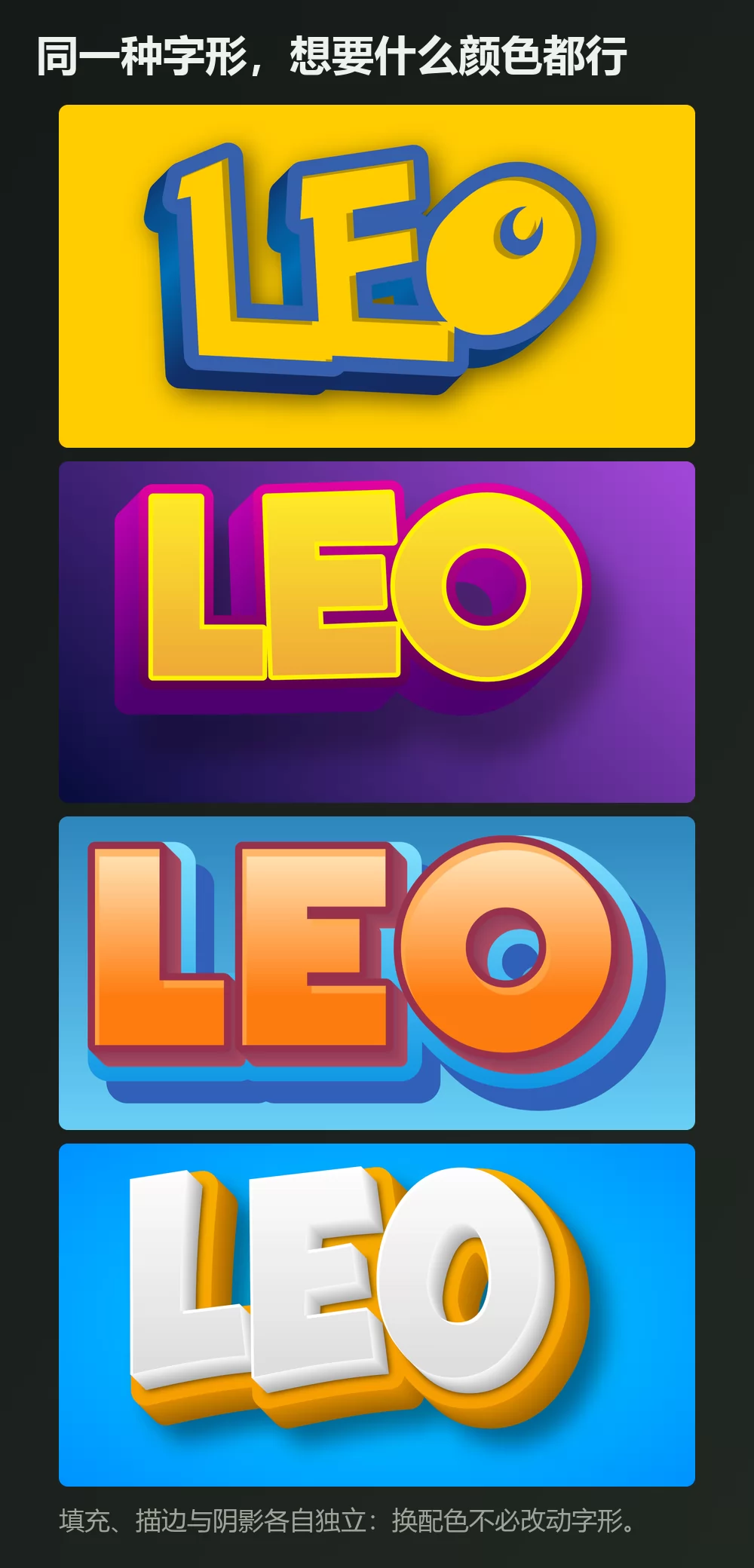
「样式」标签下有三个面板,各司其职:
- 3D 与填充负责字母本身的颜色:纯色、渐变或图案。
- 描边负责边框,包含两种立体描边。正是那圈深蓝色的边,让黄色字母读起来像宝可梦,而不是一个普通的黄色单词。
- 阴影涵盖投影、外阴影和内阴影,可调模糊与不透明度。
黄字配蓝边是这部作品的配色,但这个字形换成任何配色都成立。
第 3 步:选择尺寸
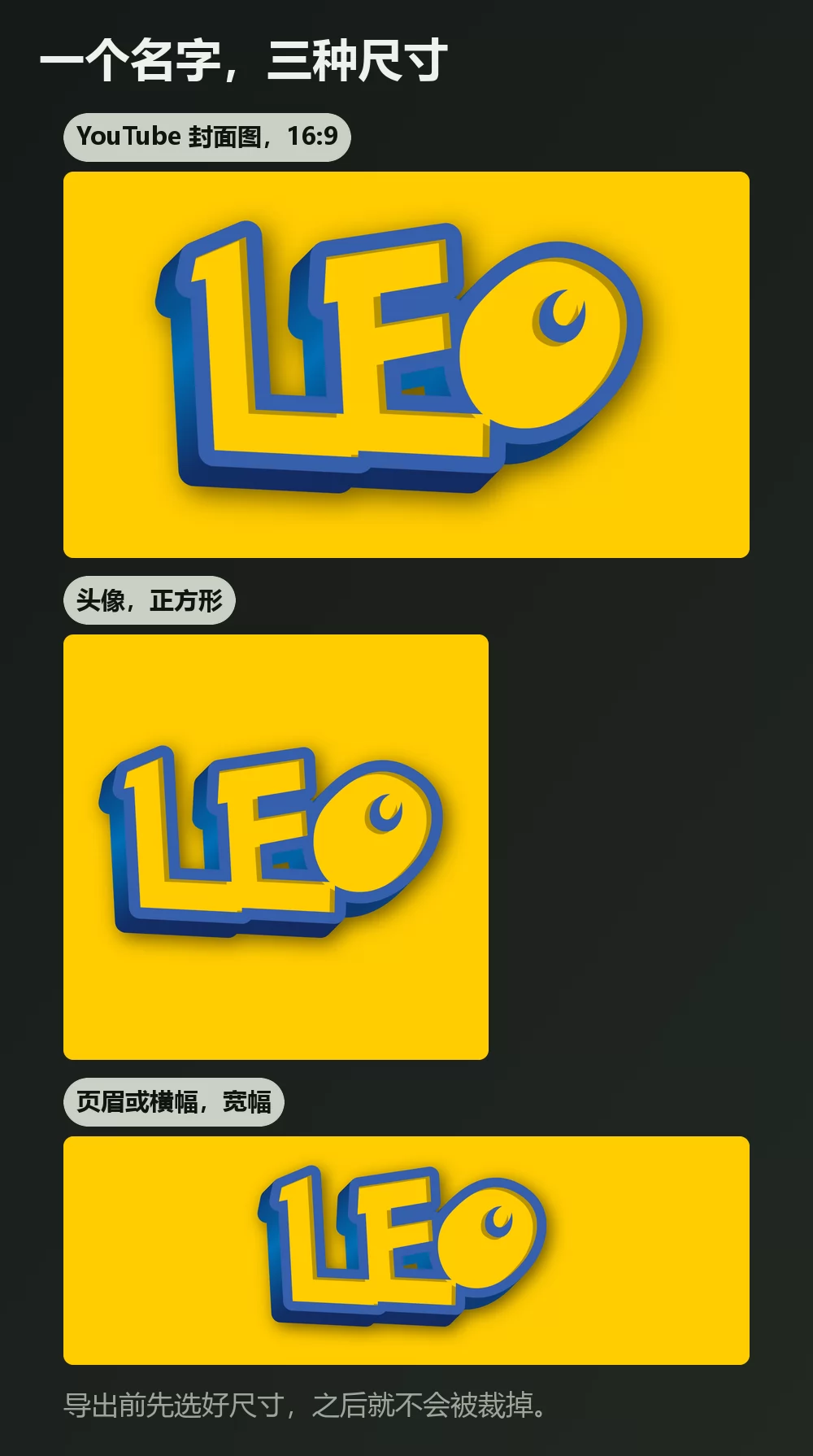
导出前先定好尺寸,之后就不会被裁掉。视频封面用 16:9,头像用正方形,页眉用宽条。
第 4 步:下载
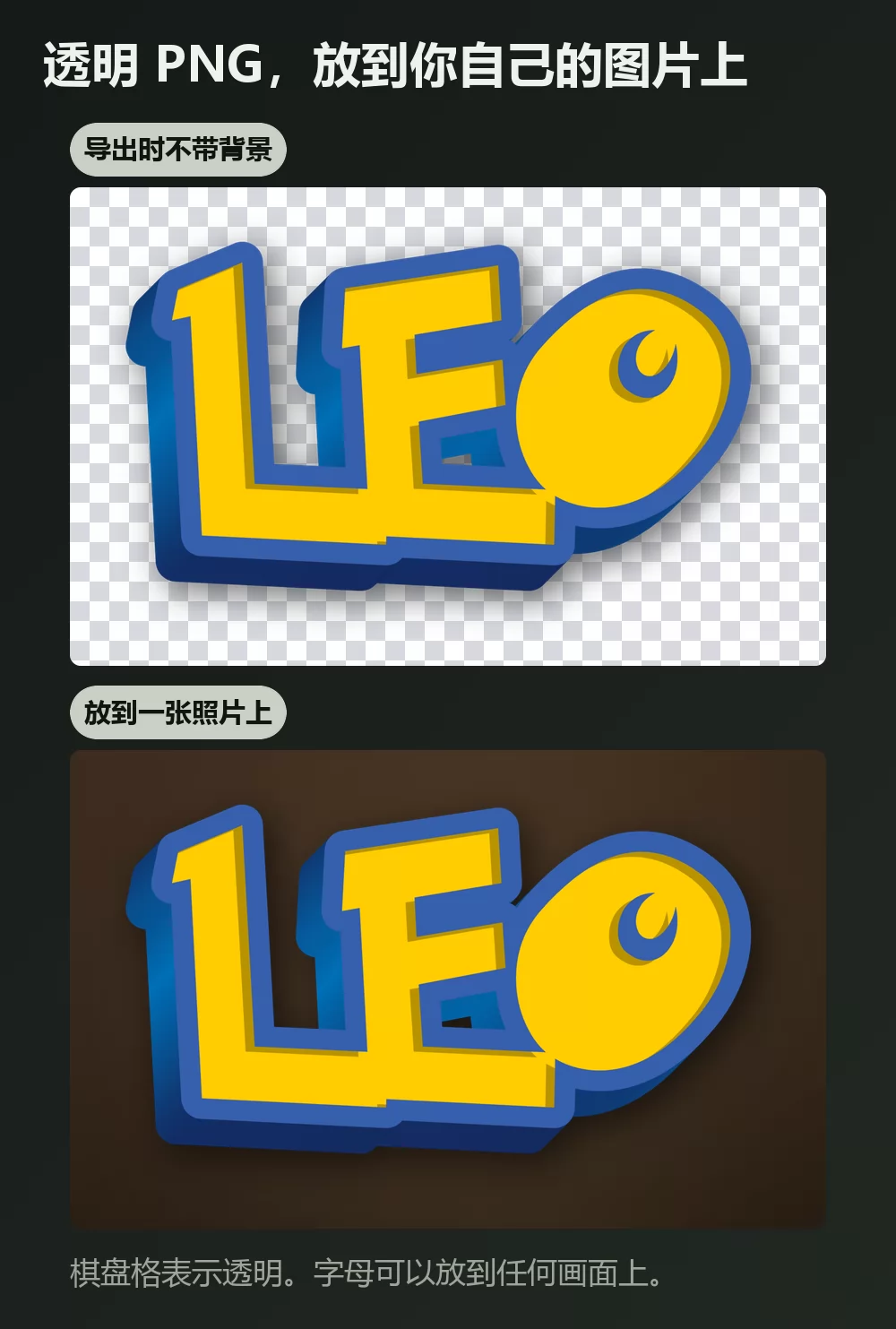
在「下载」标签里选透明 PNG,如果你打算把字母放到自己的截图、照片或封面上。这是大多数人漏掉的选项,也正是它让成品看起来是做出来的,而不是贴上去的。
名字一长,很快就占满宽度
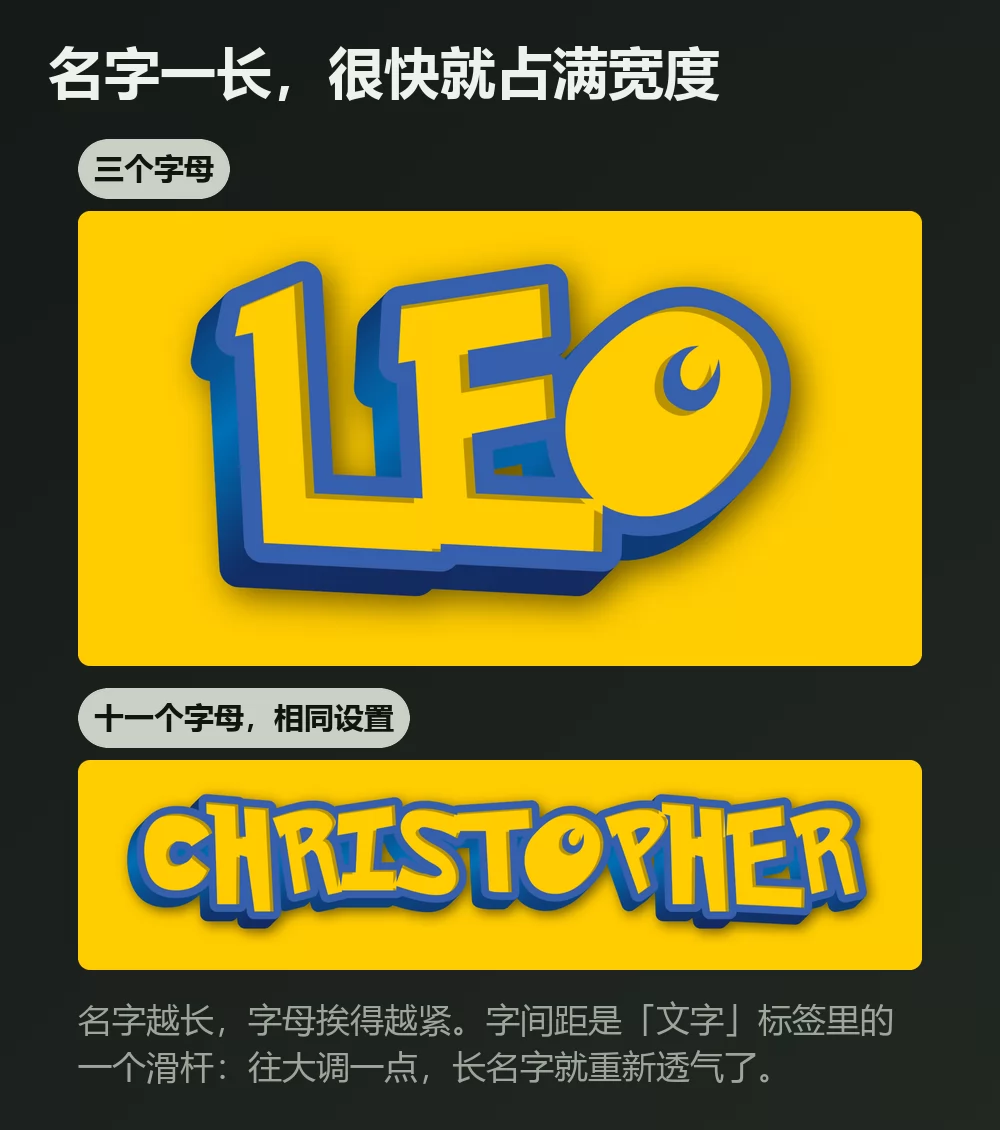
字母越多,挨得越紧。字间距是「文字」标签里的一个滑杆:往大调一点,长名字就不再显得局促。同一个标签里还有缩放、行高、弯曲和旋转。
让文字弯曲
弯曲滑杆是让标题有跃动感的关键,也是「一行平铺的字」和「像设计过的东西」之间的差别。用一点点就够:超过某个程度,字母就会呈扇形散开,名字反而难读。
要标志风格还是游戏风格?
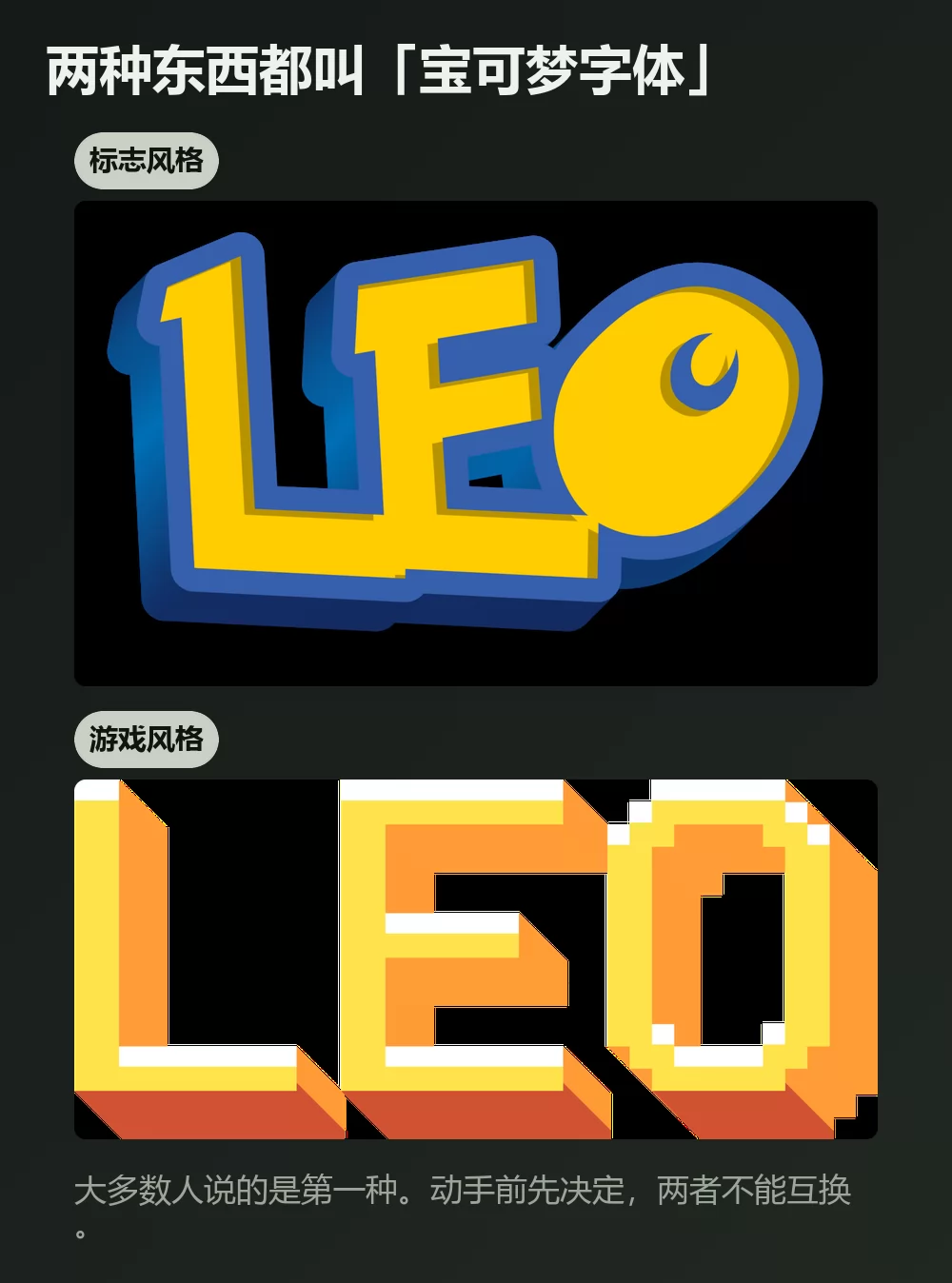
有两种不同的东西都被叫作「宝可梦字体」。大多数人说的是第一种。
标志风格是那种厚重圆润、带粗描边和一点立体感的字母,也就是上面那个生成器给你的。
游戏风格是掌机上那种细小的方块像素字。如果你要的是这种,8 位像素文字效果能带你过去。
这款字体叫 Pokemon Solid
如果你更想装一款字体、自己排文字,那就搜这个名字。DaFont 上那个直接叫「Pokemon」的粉丝复刻版,下载量已超过七百万次,提供两个文件:
- Pokemon Solid 是实心版,做标题要用它。
- Pokemon Hollow 只有轮廓,供你在大尺寸下自行填色。
有一点要有心理准备:字体只给你字母形状,别的什么都没有。蓝色描边、填充、立体感和投影都是之后要自己叠出来的效果,而这正是生成器替你做掉的活儿。
其他值得知道的宝可梦字体
- Pokemon GB 复刻了 Game Boy 游戏里的小号点阵字。做假的对话框很合适,做标题就不行。
- Pocket Monk 是标志字体的另一种诠释,如果 Pokemon Solid 不合意可以试试。
- Pokemon Pixel Font 方正、斜线呈阶梯状,更接近街机屏幕而不是这部作品。
它们全都是粉丝复刻。官方的标志手绘字是为品牌绘制的,从未作为字体发布。
在 Canva 里怎么做宝可梦文字
Canva 的字体库里没有宝可梦字体,免费版也不能自行安装。变通的做法是把字做成透明 PNG 再上传:它能直接放进 Canva 的设计里,而且依然清晰。
如果你经常用 Canva,也可以在 Canva 中直接使用 TextStudio 效果,连上传都省了。
在 Photoshop 里怎么做宝可梦文字
装上 Pokemon Solid,输入文字,然后用图层样式把这套处理重建出来:
- 描边,设为外部,深蓝色,调得厚一些。
- 渐变叠加或纯黄色填充,用于字母本身。
- 投影,向下并略微向右偏移,不透明度调低。
这样就很接近了。真正标志里的立体感来自一个复制并向后偏移的图层,要在每个字母上保持一致相当麻烦。
在 Word 里怎么做宝可梦文字
装上字体,输入文字,再用文字效果加描边和阴影。Word 的效果比图像编辑软件粗糙得多:凡是要打印或发布的东西,导出的 PNG 都会比 Word 能做出来的好看。
在手机上
在 iOS 和 Android 上,大多数应用都无法安装并使用自定义字体。生成器可以在手机浏览器里跑,所以实际可行的路径是:在手机上做好 PNG,存到相册,再在你原本用的那个应用里添加进去。
常见问题
宝可梦字体叫什么? Pokemon Solid,即粉丝复刻版的实心版。Pokemon Hollow 是同一套设计的空心轮廓版。
怎样做出宝可梦字体的文字? 在宝可梦文字生成器里输入,挑好配色,下载 PNG。十秒钟,什么都不用装。
可以换颜色吗? 可以。填充、描边和阴影各自独立,字形保持不变,配色可以完全改掉。
怎样得到透明背景? 在「下载」标签里选透明 PNG,然后把字母放到你自己的图片上。
为什么我装了正确的字体,做出来还是不像标志? 因为字体只是字母形状。蓝色描边、立体感和投影都是叠在上面的效果。